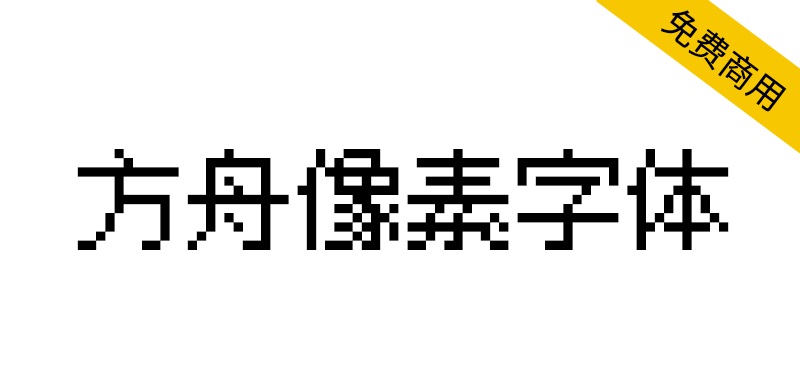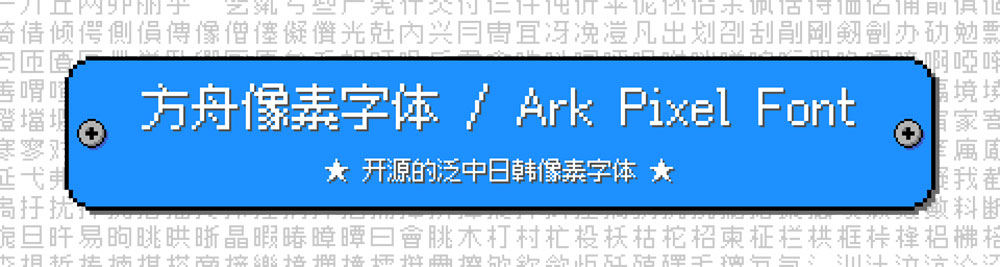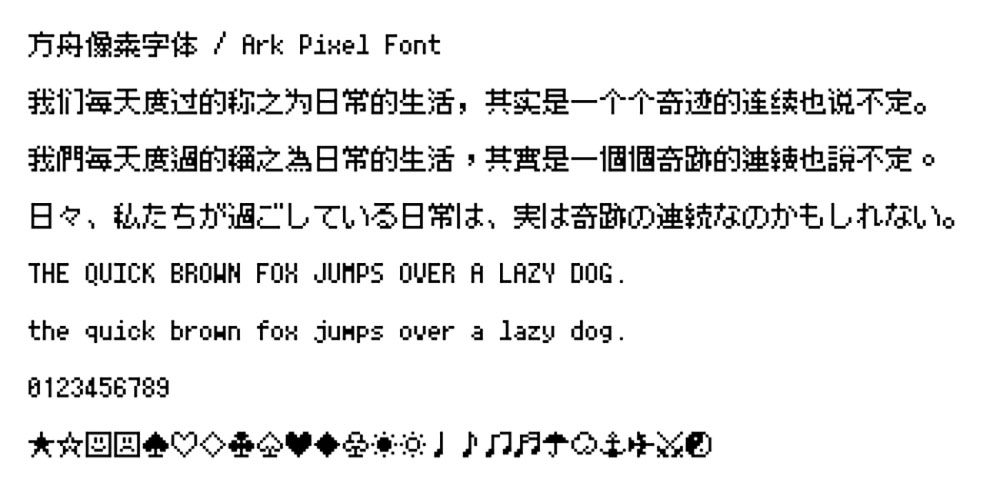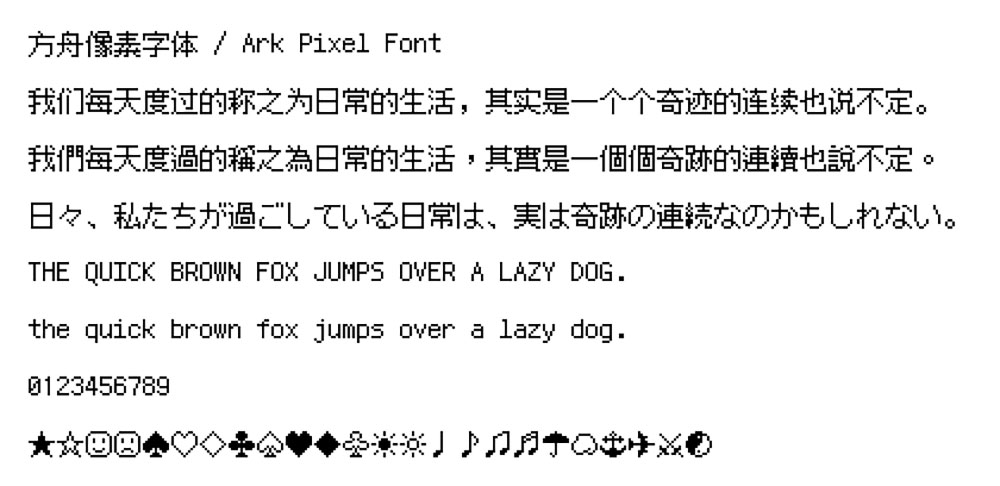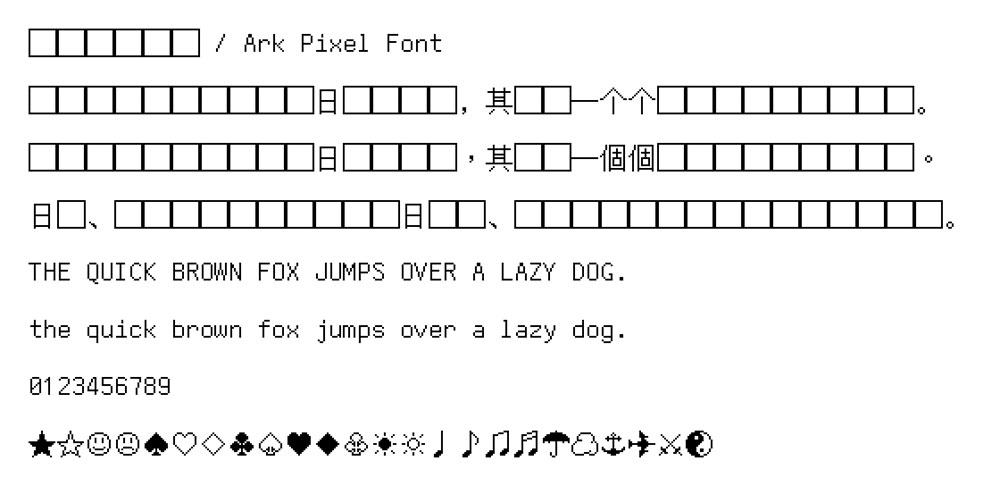
方舟像素字体是一款开源的泛中日韩像素字体,目标是为游戏开发者提供一套可用于正文的开箱即用的像素字体解决方案,使用 SIL 开放字体许可证授权。
黑体无衬线风格,支持 10、12 和 16 像素,支持语言特殊字形:中文-中国大陆、中文-香港特别行政区、中文-台湾地区、中文-传统印刷、日语、朝鲜语 。
注意:该字体目前处于积极开发阶段,仍然缺少大量汉字。生产环境请考虑临时性过渡方案:缝合像素字体